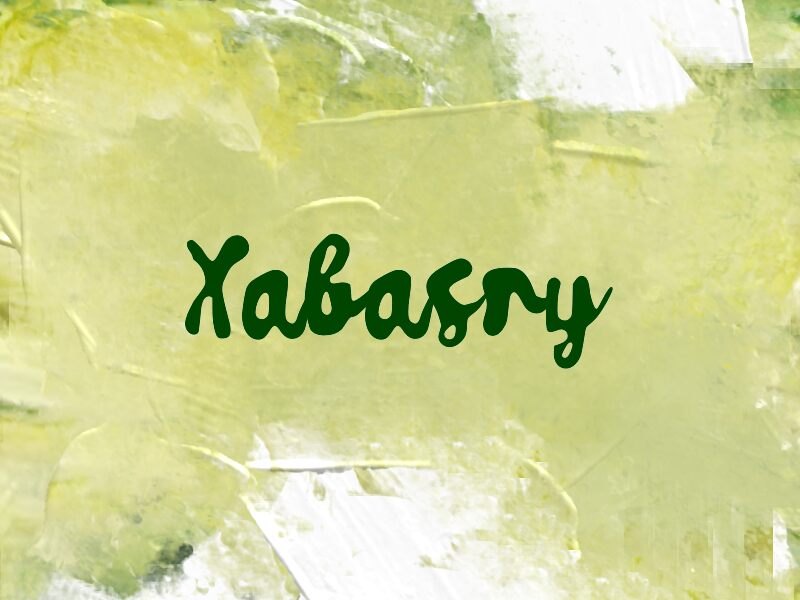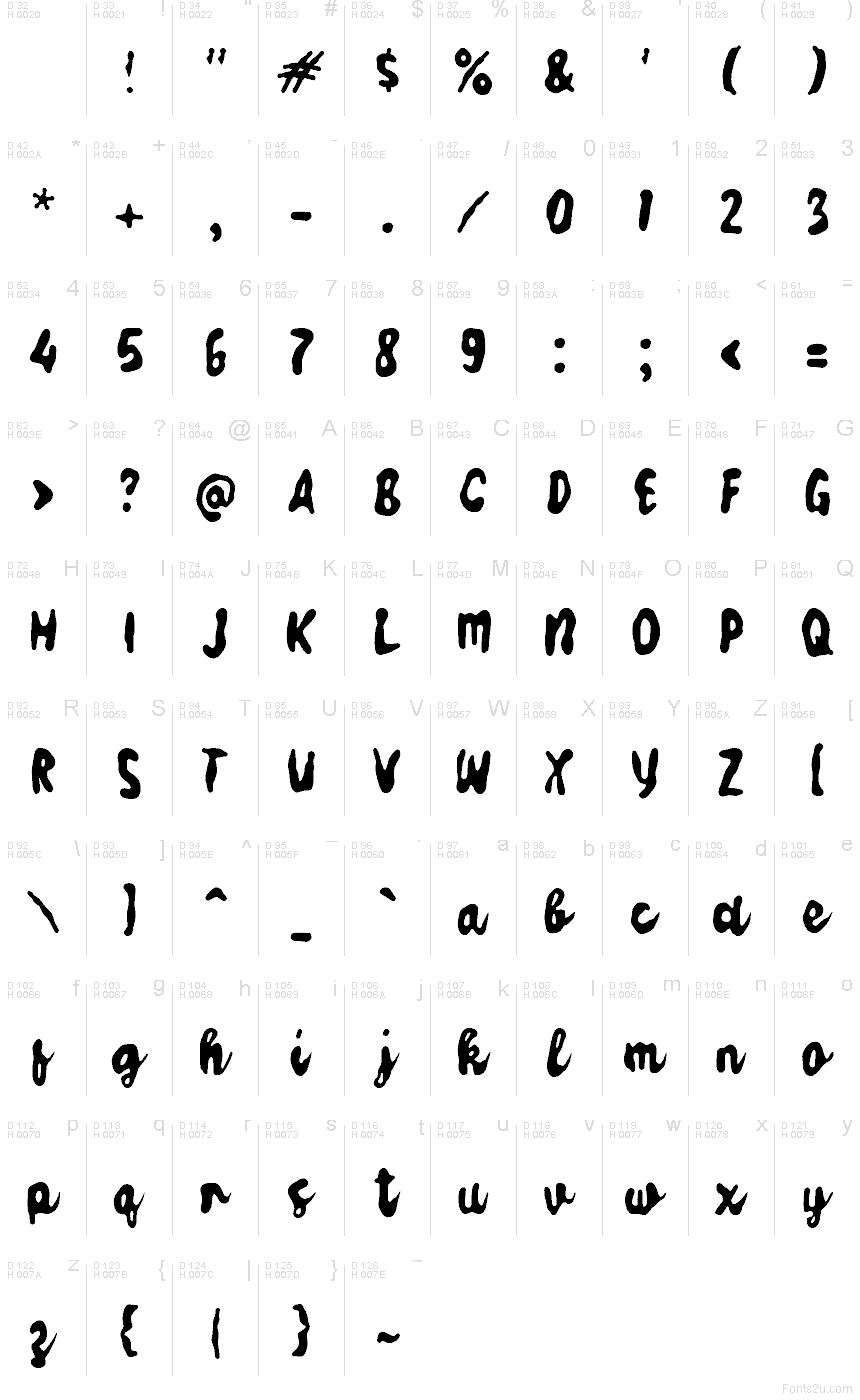
Xabasry
Xabasry от Wep — это бесплатный шрифт в стиле brush script с жирным, насыщенным «красочным» начертанием и свободным рукописным ритмом. Буквы выглядят намеренно мягкими и пухлыми, с округлыми соединениями, тяжелыми кривыми и несколькими резкими штрихами, которые не дают стилю стать слишком приторным.
Этот шрифт отлично вписывается в брендинг кафе, дизайн упаковки в стиле casual, музыкальные плакаты, заголовки для соцсетей и короткие логотипы, где характерный рукописный почерк важнее безупречной отшлифованности. Как бесплатный шрифт, он также хорошо работает в качестве заголовков на обложках, титульных карточек и для быстрых монограмм, поскольку толстые штрихи и живые повороты придают динамику даже самым коротким словам.